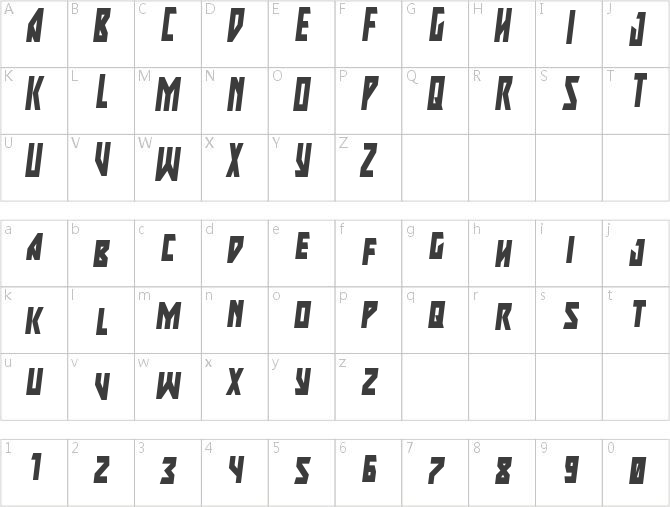
Major Force Condensed Italic
Major Force Condensed Italic介紹
Major Force Condensed Italic字體字庫是一款讓人賞心悅目、百看不厭的英文字體,適合各類廣告和產品包裝設計應用,字體大小0.02MB,格式為ttf字體,上傳用戶是小北,作者/版權方為未知